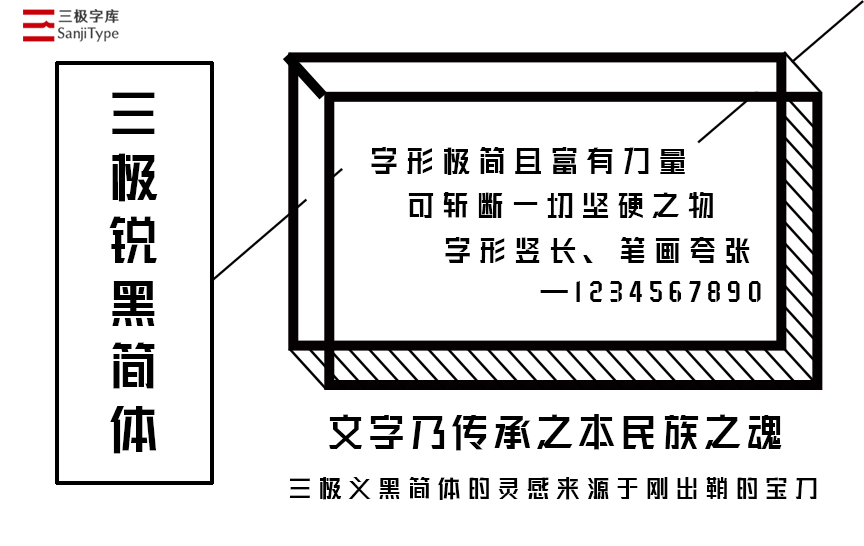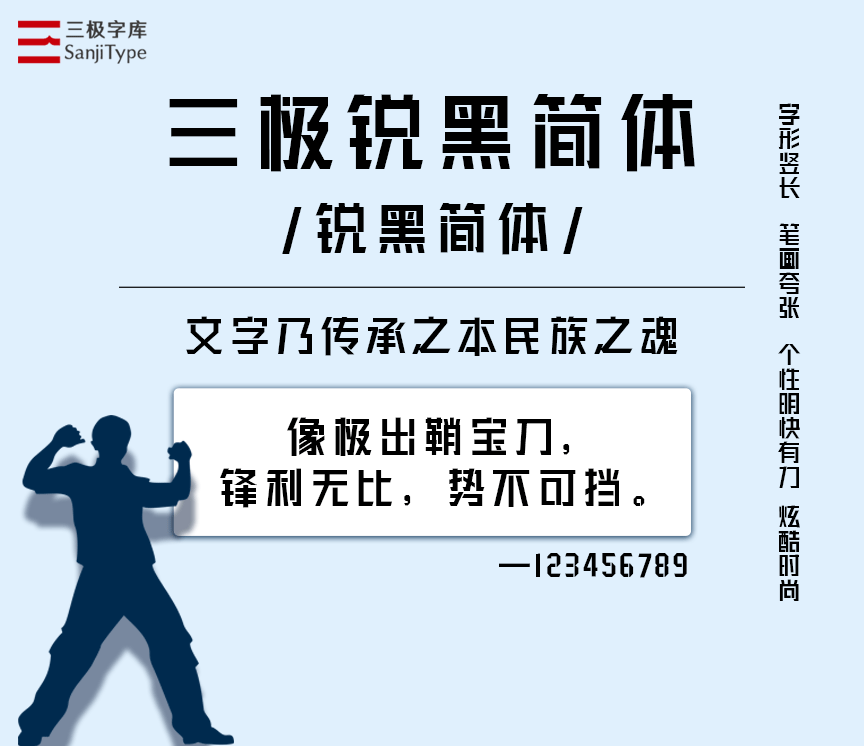
三极锐黑简体家族
字体名称:三极锐黑简体
设计师:蔡建文,蔡荣富
所属分类:黑体
三极锐黑简体的灵感来源于刚出鞘的宝刀,锋利无比、势不可挡。字形极简且富有力量,可斩断一切坚硬之物。字形竖长、笔画夸张,个性明快有力,炫酷时尚。适用于潮流时尚类的广告及产品包装设计、影视作品,界面设计。
适用媒介:杂志、书籍、广告、标志、宣传册、店招、包装、影视、动漫、游戏。